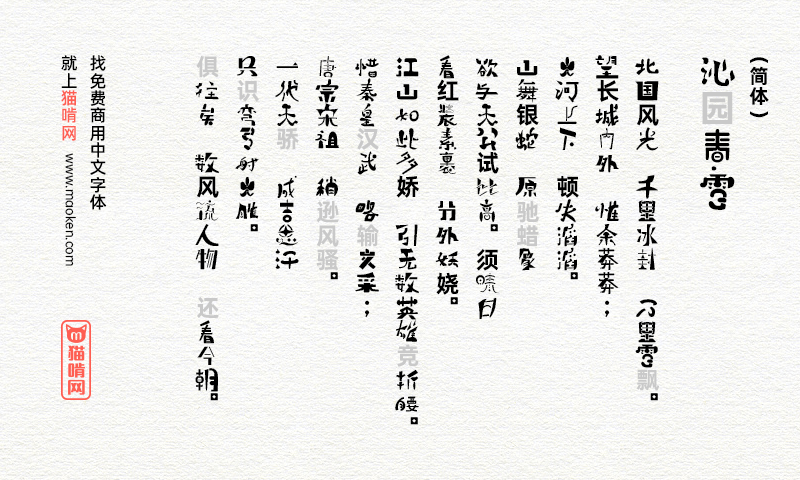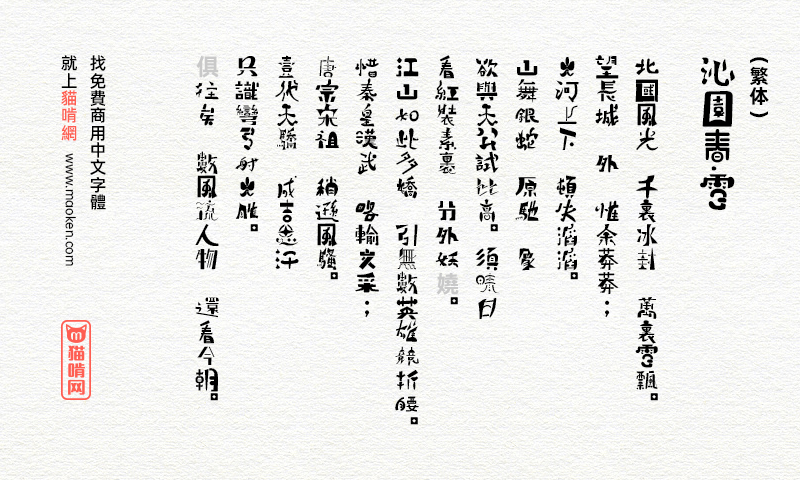
地鼠体:风格非常的狂野的免费商用字体
字体作者:もじワク研究 (其他语种) 字体字重:1个
字体名称:地鼠体(日文名:ピグモ)PS中字体名称: ピグモ 01
字体版本:Version 1.01 2016.02收录汉字:简体★★ / 繁体★★★★
字体特色
今天给大家再次带来了一款来自日本的免费字体:「 地鼠体 」 (日文名:ピグモ) 字体,它是一款风格非常的狂野的字体,设计十分有特色,对繁体中文支持较好。
它于2008年5月开始发布,截止到2016年2月,收录汉字:约 7000 个 (JIS第1水准2965字,第2水准 3390 字)